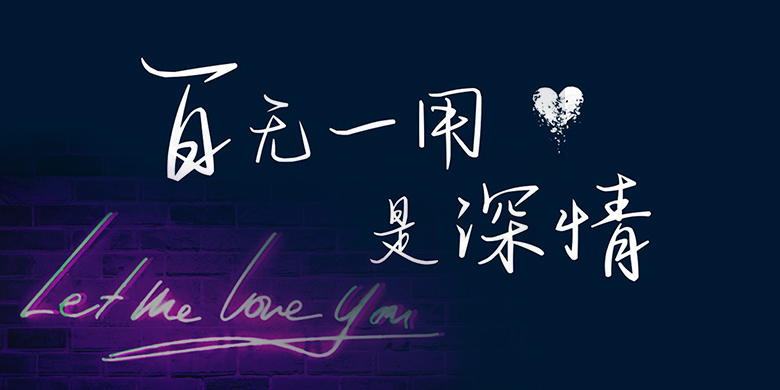
方正手迹-百无一用是深情
方正手迹-百无一用是深情,这款字体结构工整、笔画清晰,兼顾美观与易读性,适用于标题、正文、海报、包装、LOGO 等多种场景。字形优雅稳定,风格百搭耐看,适配日常排版与创意设计,让文字呈现更舒适、更具质感。方正手迹-百无一用是深情一笔一画,皆是细节,以均衡的比例、流畅的线条打造舒适视觉体验,字形端正大气,风格简约现代。无论是商业设计、品牌宣传还是日常排版,都能轻松驾驭,让文字更有格调与力量。方正手迹-百无一用是深情字体下载。
百无一用是深情是一款连笔较多的手写字,笔画连贯流畅,文艺清新。结构紧凑,中宫收紧,笔画舒展。适用于文艺类的书刊、品牌广告和产品包装设计,以及社交网络的个性化用字。